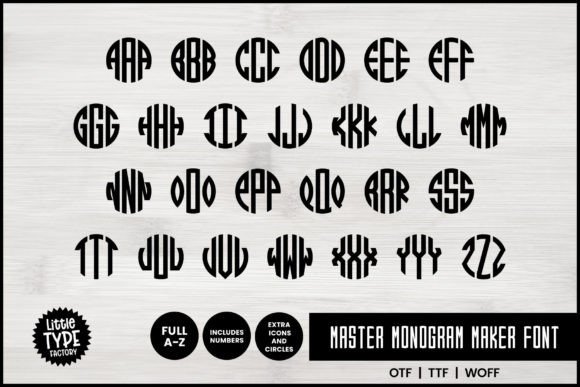
Master Monogram
การค้นหาองค์ประกอบการออกแบบที่เหมาะสมอาจเป็นเรื่องท้าทาย แต่ Master Monogram นำเสนอคอลเลกชันที่โดดเด่นซึ่งช่วยยกระดับงานของคุณได้ทันที
ไม่ว่าคุณจะสร้างผลิตภัณฑ์ POD (Print on Demand) คำเชิญงานแต่งงาน หรือกราฟิกโซเชียลมีเดีย Master Monogram ก็เหมาะสมอย่างยิ่ง